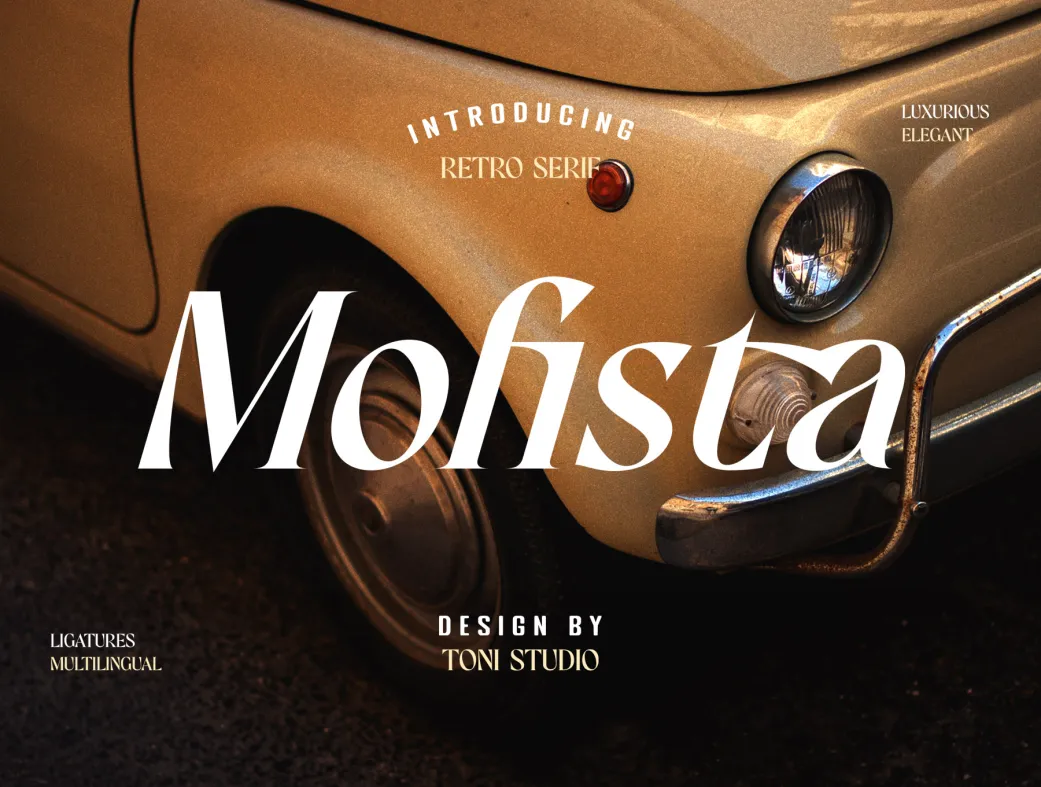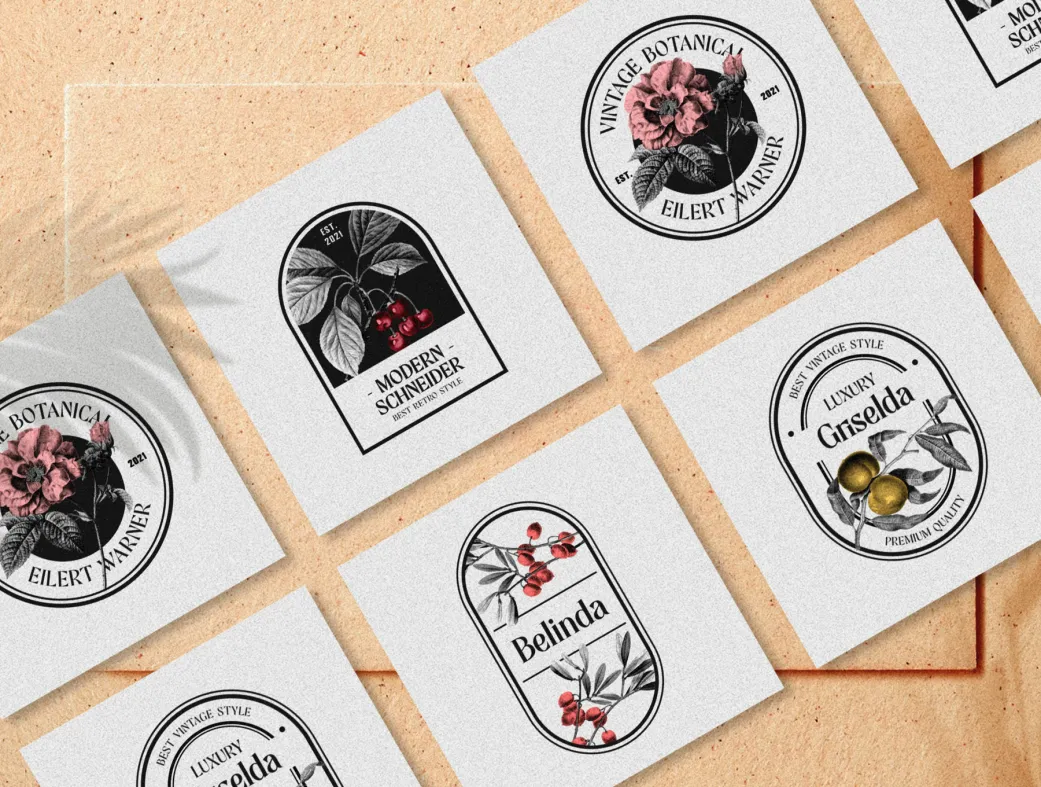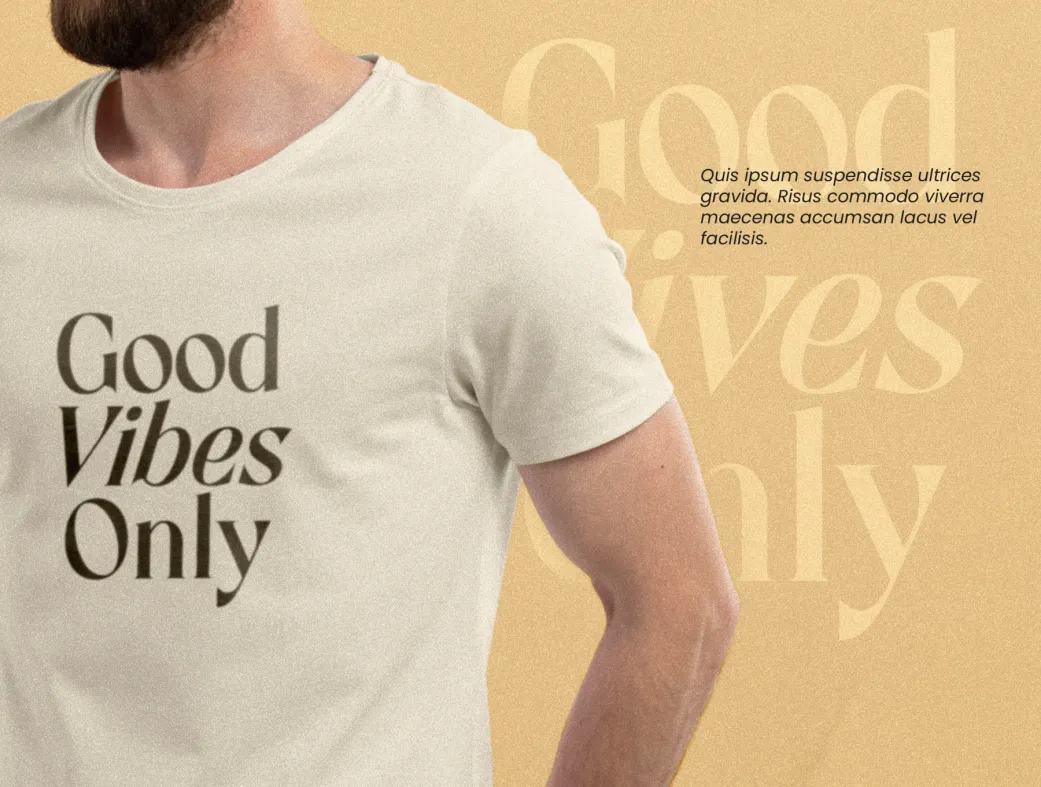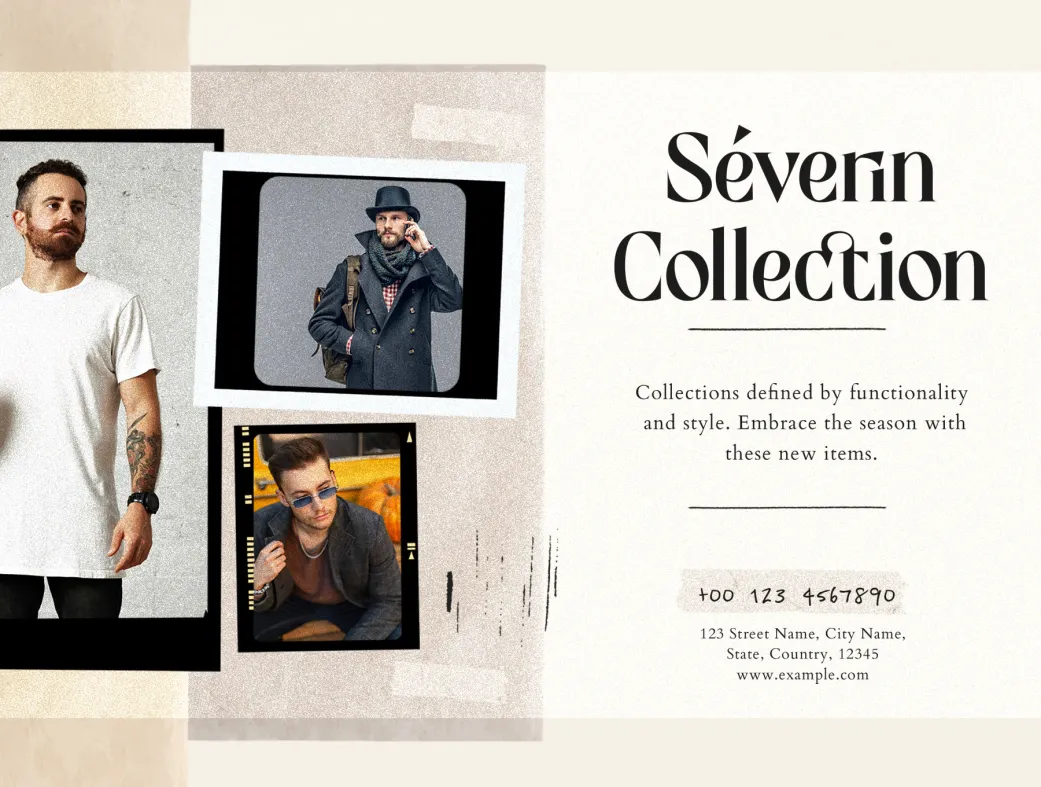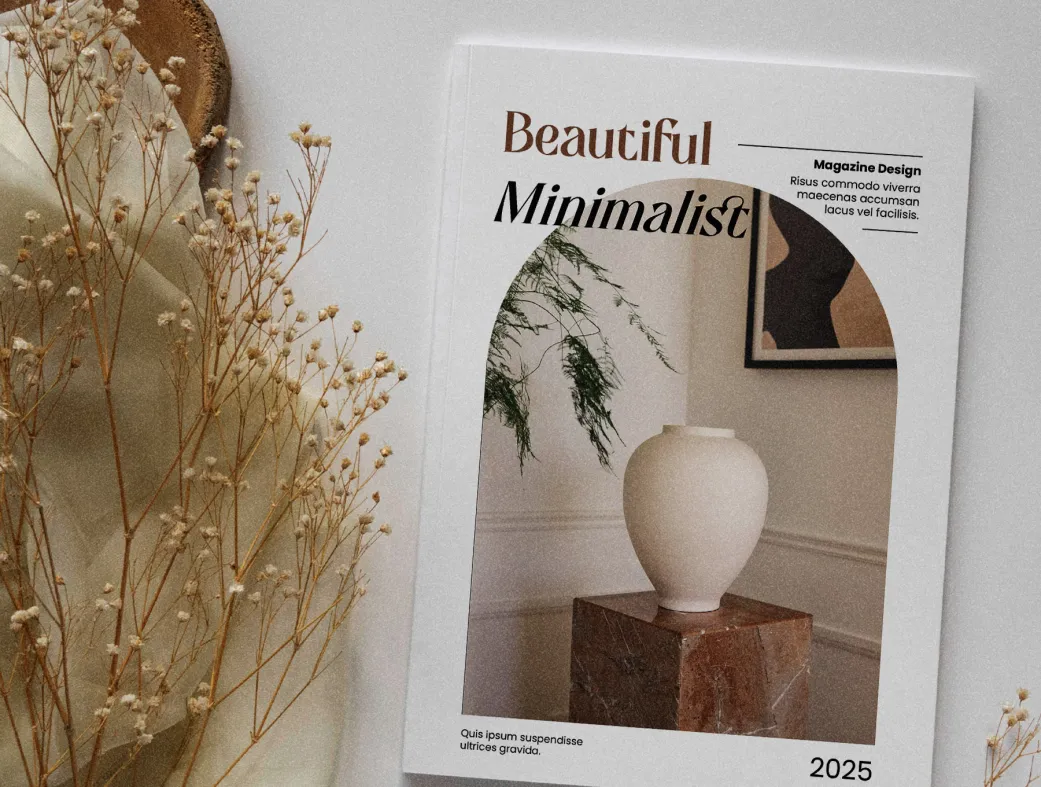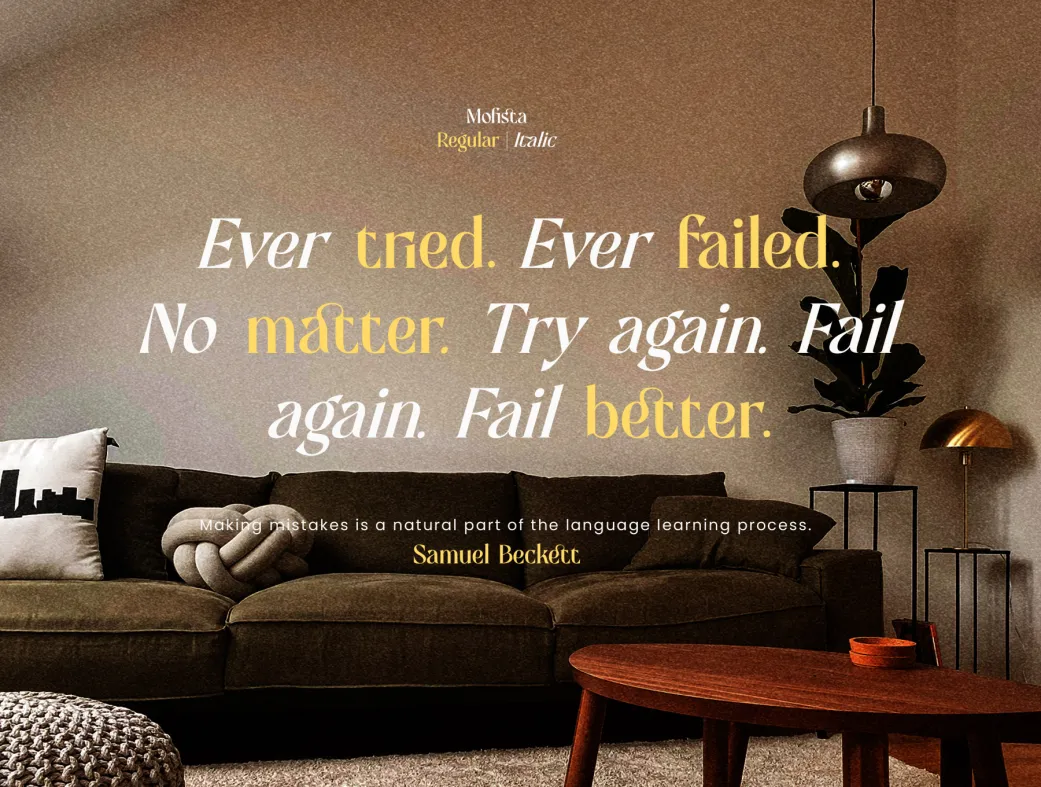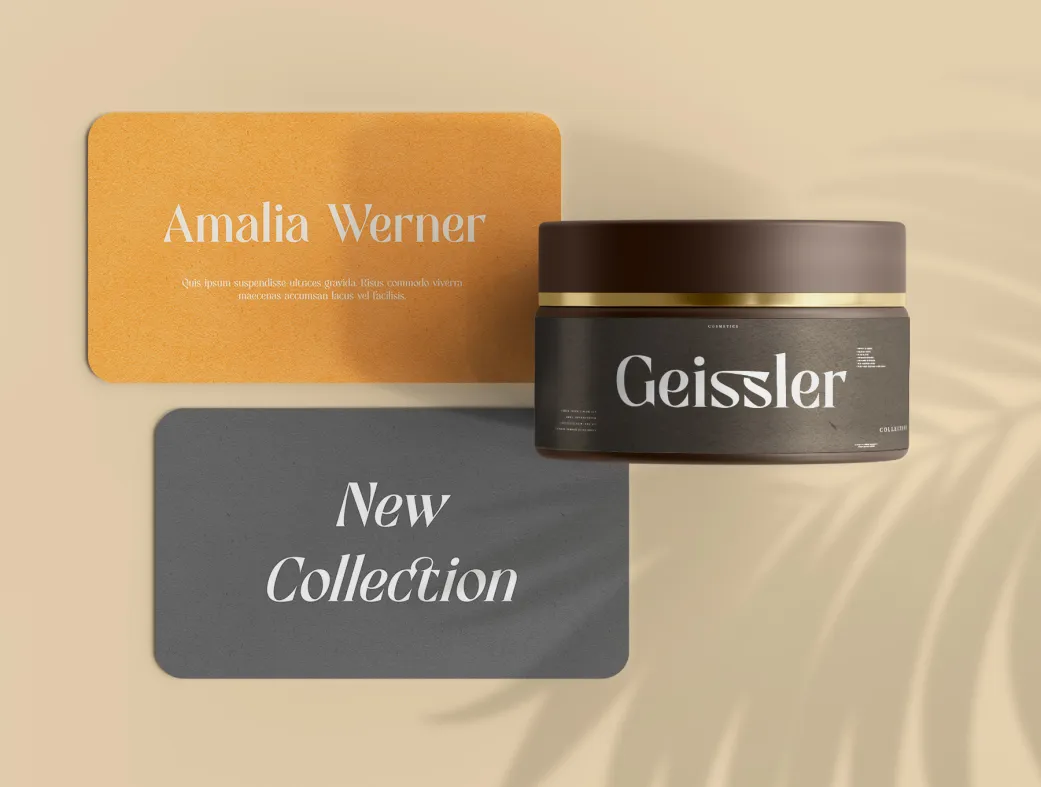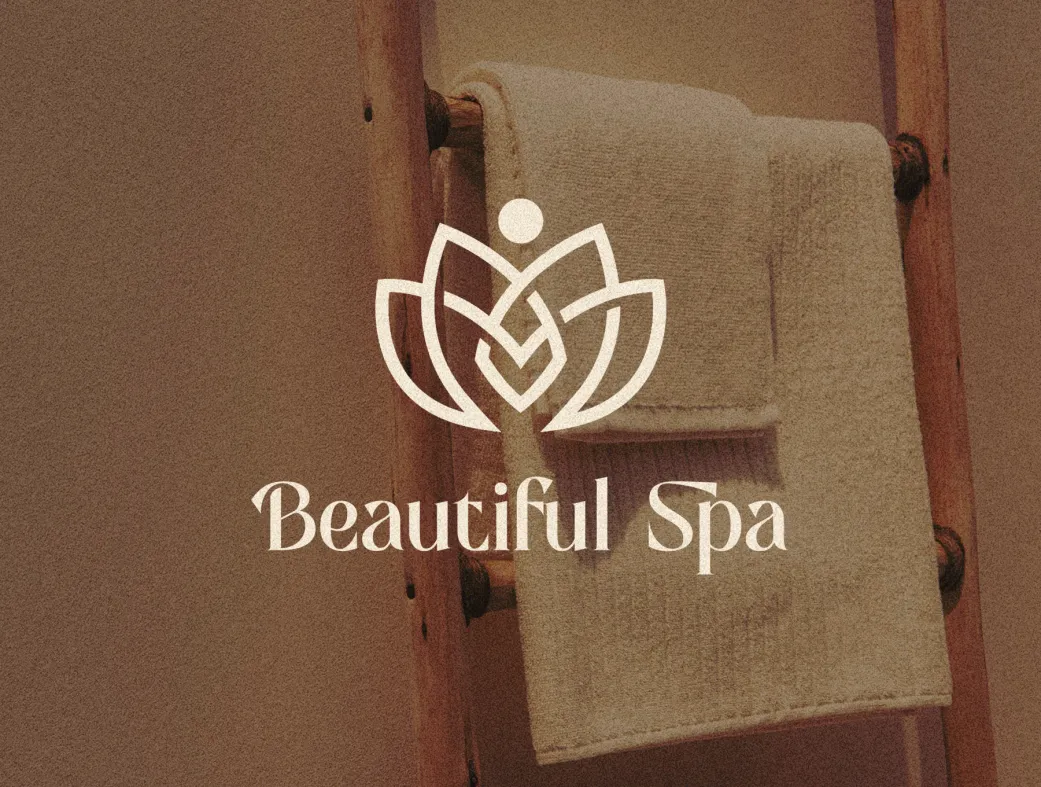
فونت سریف مدرن موفیستا | Mofista
آیا به دنبال زیبایی و نوستالژی در طراحی هستید؟ فونت موفیستا با ظاهری شیک و مدرن، پروژه‌های شما را به سطح جدیدی از جذابیت می‌برد!
Mofista-Modern Serif Typeface
فونت سریف مدرن موفیستا | Mofista | Mofista Font
معرفی محصول:
فونت سریف مدرن موفیستا، یک نوع‌خط نوستالژیک و مدرن است که به طراحی‌های کلاسیک و پر از احساسات احترام می‌گذارد. این فونت با طراحی‌های جایگزین خود، به ارائه‌ها و لوگوهای شما جلا و جذابیت بیشتری می‌بخشد. موفیستا با ظاهری شیک و مرتب، پروژه‌های شما را به یک سطح جدید از زیبایی و خلاقیت می‌برد.
ویژگی‌ها و مزایا:
فونت موفیستا (در دو حالت Regular و Italic) با حروف بزرگ و کوچک، اعداد و نشانه‌گذاری، و همچنین حروف جایگزین، مجموعه‌ای کامل برای طراحی‌های شما به شمار می‌رود. طراحی نرم و دلپذیر سریف‌ها به این فونت گرما و نوستالژی خاصی می‌بخشد و می‌تواند به پروژه‌های شما شخصیت و جذابیت بیشتری اضافه کند. این فونت برای انواع پروژه‌ها از جمله دعوتنامه‌ها، کارت‌پستال‌ها، پوسترها، کتاب‌ها، تبلیغات، وب‌سایت‌ها، سرصفحه‌های وبلاگ، لوگوها، برندها، مجلات، مد و عکاسی مناسب است.
کاربردها و نکات استفاده:
فونت موفیستا مناسب برای طراحان حرفه‌ای و مبتدی است. طراحان می‌توانند از این فونت برای ایجاد هویت بصری قوی و جذاب بهره ببرند، در حالی که مبتدیان نیز می‌توانند به راحتی از آن در پروژه‌های خود استفاده کنند. برای بهترین نتیجه، پیشنهاد می‌شود از این فونت در طراحی‌های با تم‌های نوستالژیک و مدرن بهره ببرید.
1. آیا فونت موفیستا چند زبانه است؟
بله، فونت موفیستا از پشتیبانی چند زبانه برخوردار است و می‌توانید در زبان‌های مختلف از آن استفاده کنید.
4. آیا می‌توانم حروف جایگزین را در موفیستا استفاده کنم؟
بله، موفیستا شامل حروف جایگزین است که می‌توانید برای تنوع بیشتر در طراحی‌های خود از آن‌ها استفاده کنید.